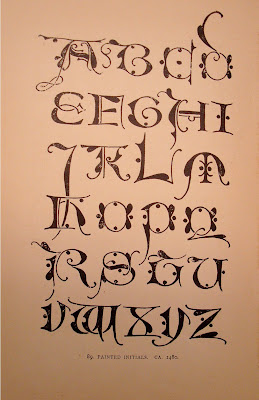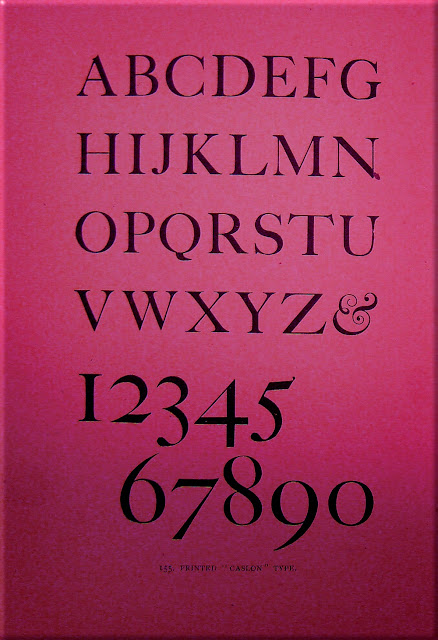
| Lewis F. Day (1845 - 1910) |
LEWIS FOREMAN, DAY.
Bonito libro sobre la historia de los alfabetos y con muchísimos ejemplos de todas las épocas, escuelas y calígrafos. Podéis disponer on-line de este libro y leerlo, vale la pena darle un vistazo con tranquilidad ya que contiene mucha información interesante.
La caligrafía fue un arte esencial en su trabajo:
Bien como siempre, añado una serie de fotografías de este libro que reproduce al final unas curiosas láminas dedicadas al "Amperzand (&)" y ha diferentes modelos de números:
Alfabetos Antiguos:
| Tapas de estilo modernista |
![]() |
| Portada |
![]() |
| Alfabeto Griego, Impreso en Basel, s. XVI |
![]() |
| Abecedario Anglo-Sajón S. VII |
![]() |
| Alfabeto Irlandés del libro de Kells s.VIII |
![]() |
| Alfabeto Irlandés del libro de Kells s. VIII, coloreado |
![]() |
| Alfabetos de misales anglo-sajones entre s. VIII y IX |
![]() |
| Alfabeto de un misal del s. X |
![]() |
| Alfabeto Inglés de finales del s. XII |
![]() |
| Alfabeto Inglés de finales del s. XII, (coloreado) |
![]() |
| Alfabeto del s XII, Lisbjerg, Dinamarca |
![]() |
| Alfabeto del s XII, Lisbjerg, Dinamarca, (Coloreado) |
![]() |
| Alfabeto de una Biblia del s. XIII |
![]() |
| Alfabeto de un misal inglés, 1400 ca. |
![]() |
| Alfabeto de un misal inglés, 1400 ca. (coloreado) |
![]() |
| Abecedario de 1475 ca. |
![]() |
| Capitulares, ca. 1480 |
![]() |
| Capitulares, ca. 1480, coloreadas |
![]() |
| Inscripciones Alemanas y Capitulares de finales del s XV |
![]() |
| Alfabeto de un manuscrito del s. XVI |
![]() |
| Capitulares de un libro de coro de Monte Casino, Italia, s,XVI |
![]() |
| Capitulares de un libro de coro de Monte Casino, Italia, s,XVI, (Negativo, coloreado) |
![]() |
| Alfabeto de Durero, principios del s. XVI |
![]() |
| Alfabeto de Durero, principios del s. XVI |
![]() |
| Alfabeto italiano entre el s.XV y s. XVI |
![]() |
| Alfabeto de Vicentino 1523 |
![]() |
| Alfabeto de Vicentino, 1523 |
![]() |
| Alfabeto de Vicentino, 1523,(Negativo y coloreado) |
![]() |
| Alfabeto Hoffer, 1549 |
![]() |
| Alfabeto, Cresci, 1570 |
![]() |
| Alfabeto, Cresci, 1570, (Negativo y coloreado) |
![]() |
| Alfabeto, Cresci, 1570 |
![]() |
| Alfabeto Flamenco de 1579 y otro grabado sobre piedra del s XVII |
![]() |
| Bingen 1576,1598 y 1618 |
![]() |
| Itálicas, del s. XVII |
![]() |
| Itálicas, del s. XVII |
![]() |
| Alfabeto de C. Snell, 1715 |
![]() |
| Alfabeto Andrade de Figueiredo, 1721 |
![]() |
| Tipos Caslon, ( Mayúsculas) |
![]() |
| Tipos Caslon, Mayúsculas(Coloreado) |
![]() |
| Tipos Caslon , Minúsculas y cursiva |
![]() |
| Alfabeto Hebreo, (Paleografía de Silvestre) |
![]() |
| Alfabeto Hebreo >>>>>>>>>>>>>><<<<<<<<<<<< |
![]() |
| Alfabeto de Walter Crane, coloreado |
![]() |
| Alfabeto de Otto Hupp |
![]() |
| Alfabeto de Lewis Foreman. Day |
![]() |
| Alfabetos de Lewis Foreman. Day |
![]() |
| Alfabeto de Lewis Foreman. Day, (coloreado) |
![]() |
| Alfabeto de Alfred Carpenter y Lewis Foreman. Day |
![]() |
| Alfabeto de Lewis Foreman. Day |